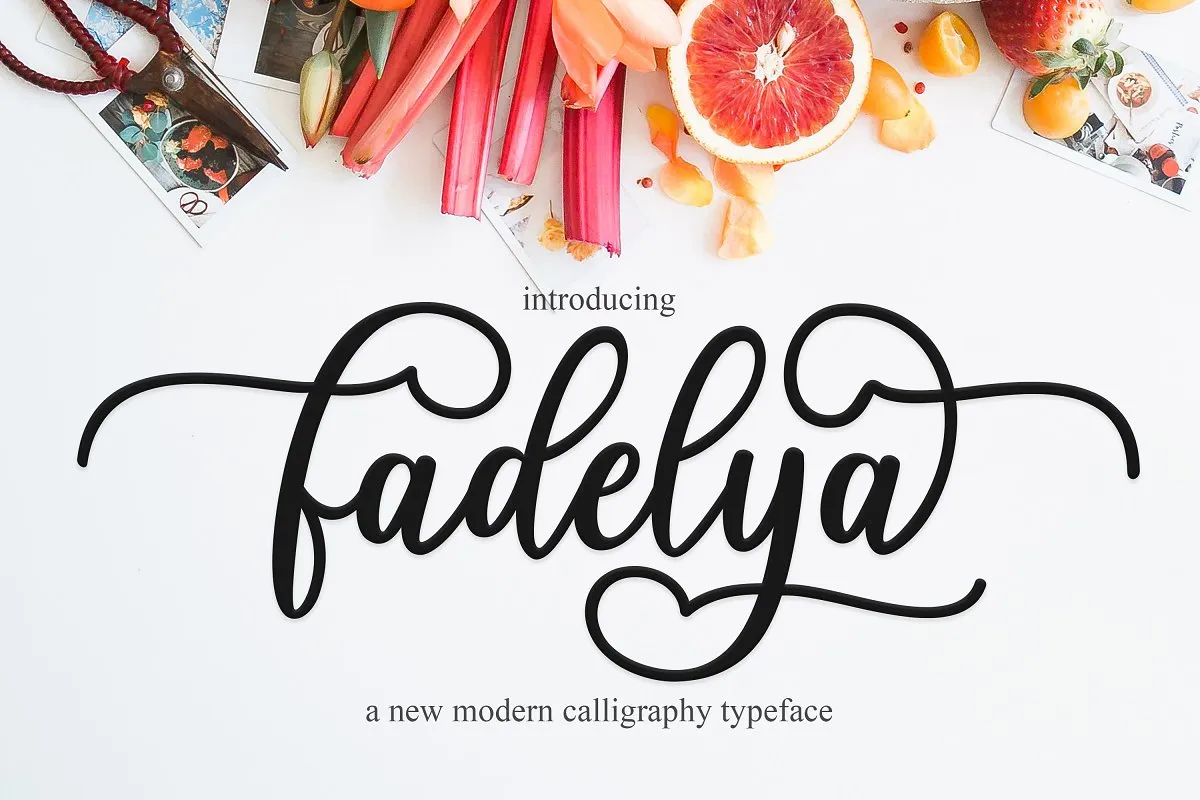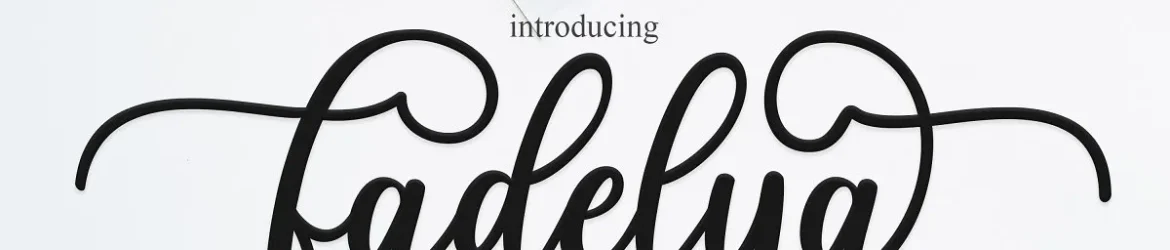
A Fadelya Script Font é uma nova fonte com estilo de escrita feito à mão moderno inspirado no vintage. Ela é perfeita para criações variadas, desde branding e cartões de visita até decoração de interiores, como posters e capas de revistas. Inspirada na forma atual da escrita cursiva e com swashes sofisticados, a Fadelya oferece uma alta qualidade que se ajusta perfeitamente à tendência moderna do design. Essa fonte é ideal para aqueles que desejam dar um toque único em suas criações. Se você está procurando por uma fonte moderna e elegante com um toque nostálgico, a Fadelya Script pode ser sua escolha. Suas curvas fluidas se destacam entre outros tipos de fontes, tornando-a perfeita para uso em materiais publicitários como cartões de visita ou embalagens de produtos. Além disso, ela é ideal para criações mais pessoais, como cartões de aniversário ou decoração de casamentos. A Fadelya Script foi projetada pelo designer zziplex e apresenta um mix perfeito entre modernidade e nostalgia, tornando-a uma escolha atraente para designers gráficos que buscam um estilo único. Ela é certamente capaz de dar ao seu trabalho o toque diferenciado que você está procurando.